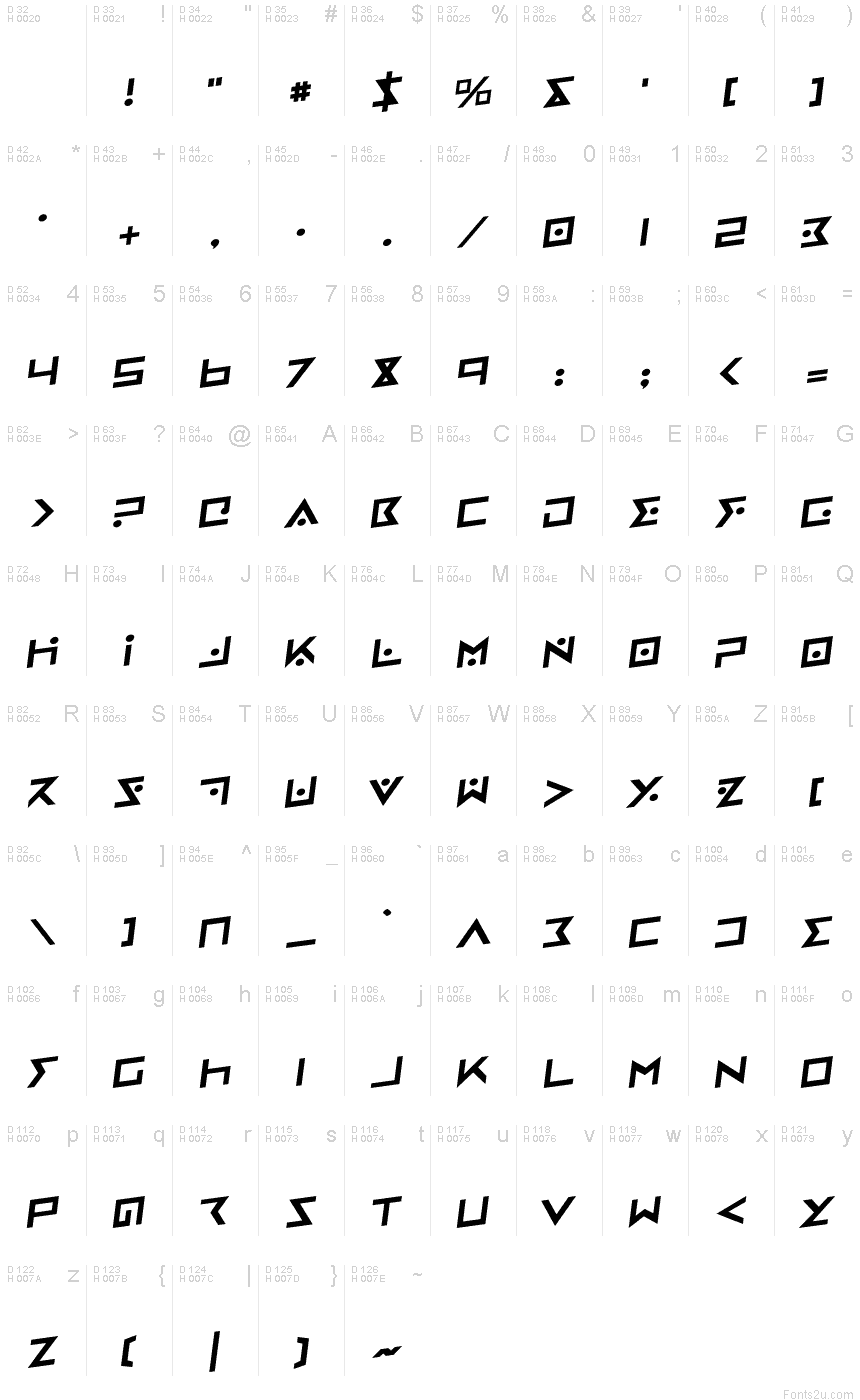
Iron Cobra Rotalic od Iconian Fonts to darmowy, futurystyczny krój pisma typu display o ostrym, dynamicznym charakterze. Litery są wycięte w ostre przekątne i otwarte kąty, które sprawiają wrażenie szybkości i mechanicznej precyzji, nadając krojowi elegancki sznyt science-fiction zamiast neutralnego, technicznego wyglądu.
Naturalnie sprawdzi się w logo gier, ulotkach muzyki elektronicznej, nagłówkach plakatów, planszach streamingowych oraz brandingu inspirowanym interfejsami, gdzie potrzebny jest darmowy font z ruchem i napięciem. Użyj go do krótkich nazw, tekstów na okładki i kompaktowych znaków graficznych – strome pochylenie i wyrazista geometria nadają nawet krótkim tekstom naładowaną energią, szybką sylwetkę.
Iron Cobra Rotalic